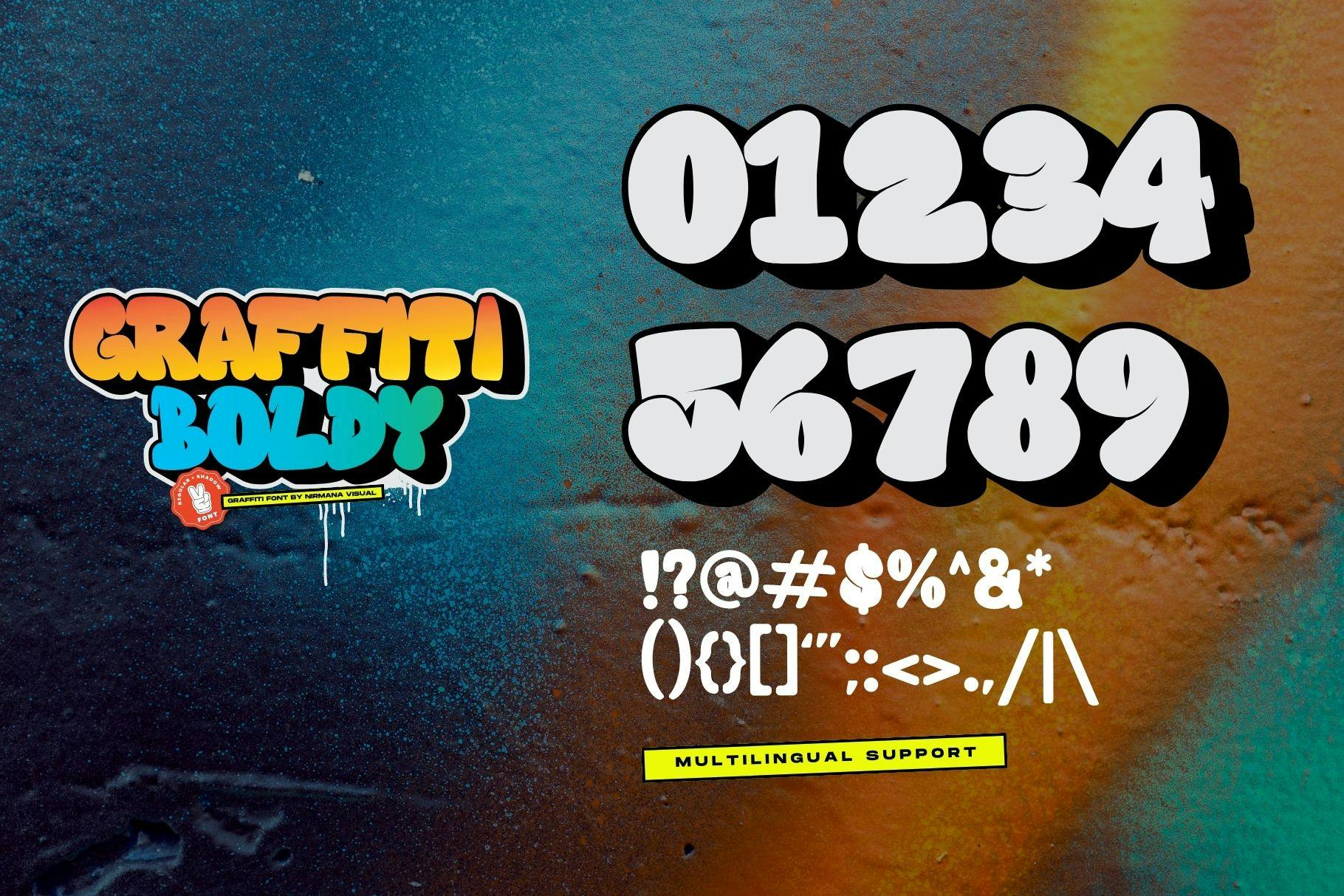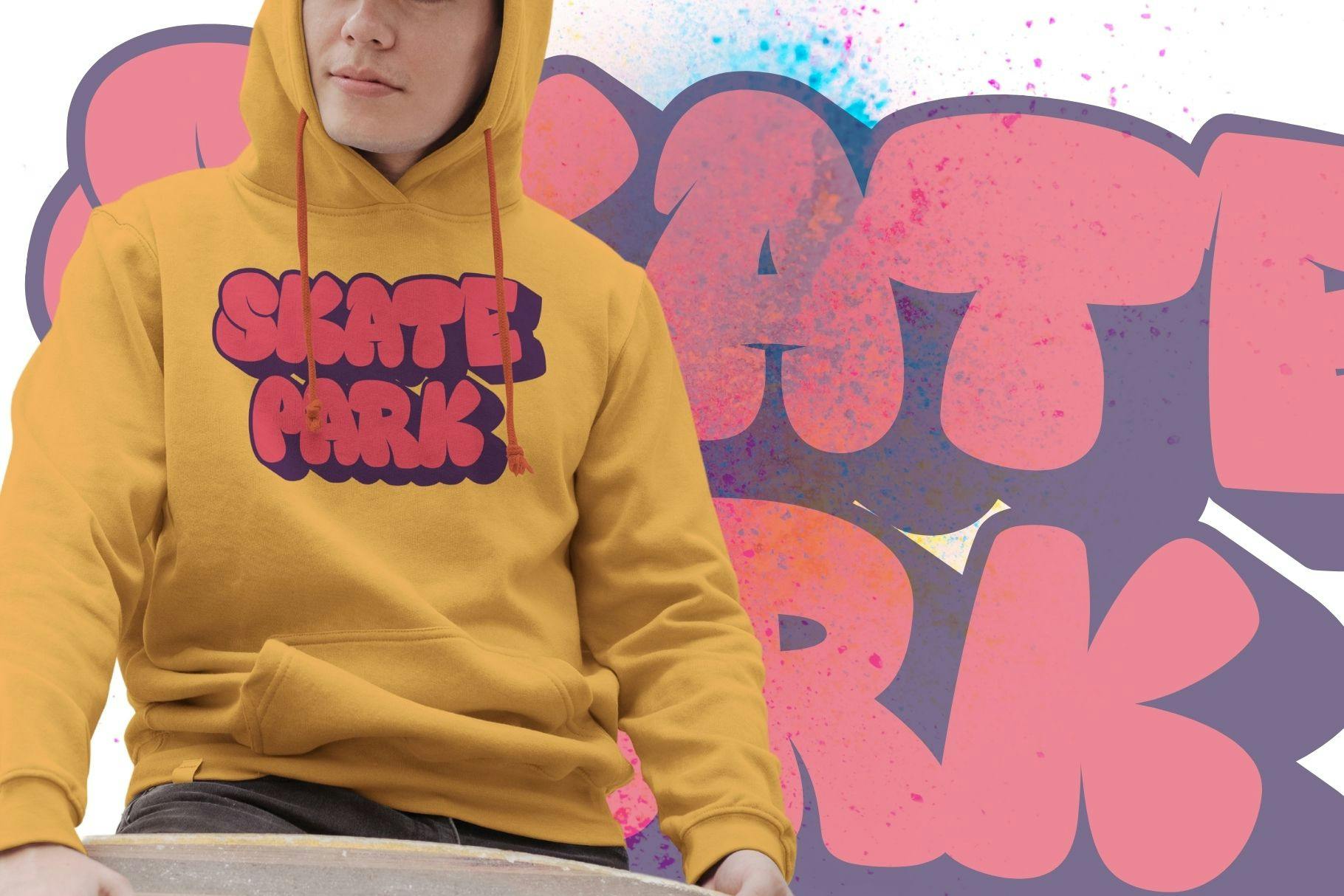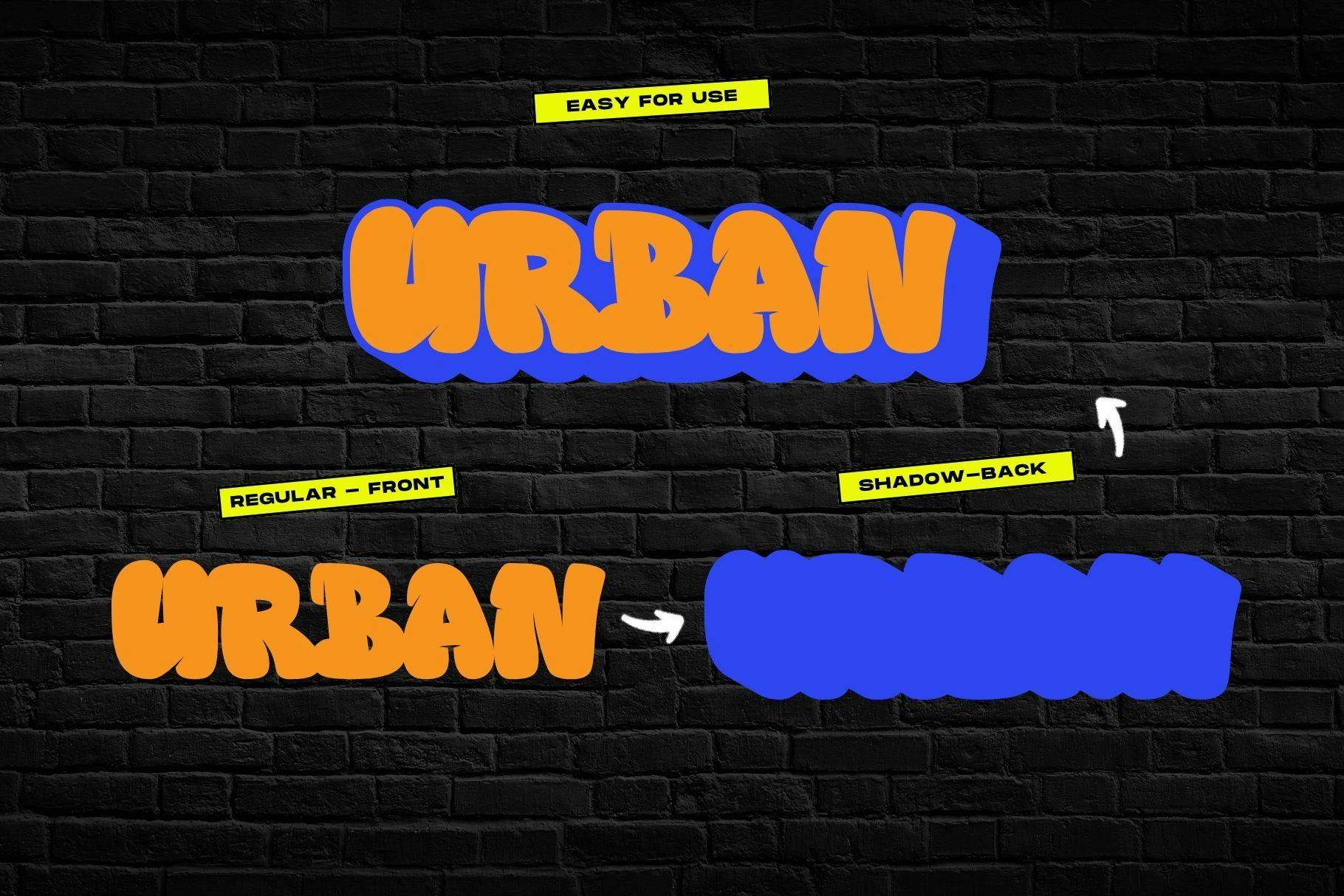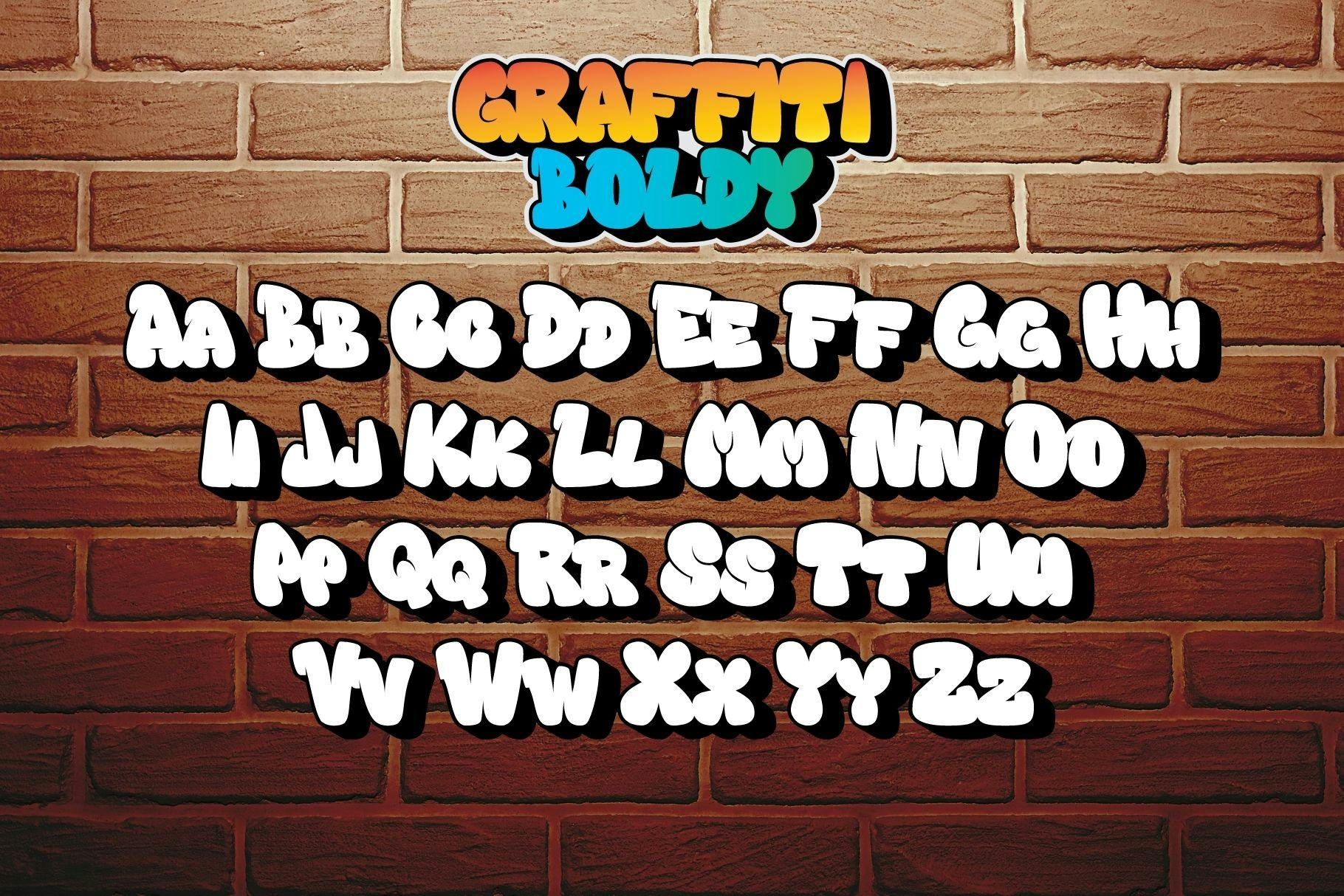
آشنایی با فونت گرافیتی بولدی
الهامگرفته از طراحی سبک گرافیتی، با ۲ استایل: معمولی و سایه
فونت گرافیتی بولدی ترکیب زیبایی از هارمونی تایپوگرافی را برای پروژههای طراحی متنوع، از جمله لوگو و برندینگ، پستهای شبکههای اجتماعی، تبلیغات و طراحی محصولات ارائه میدهد.